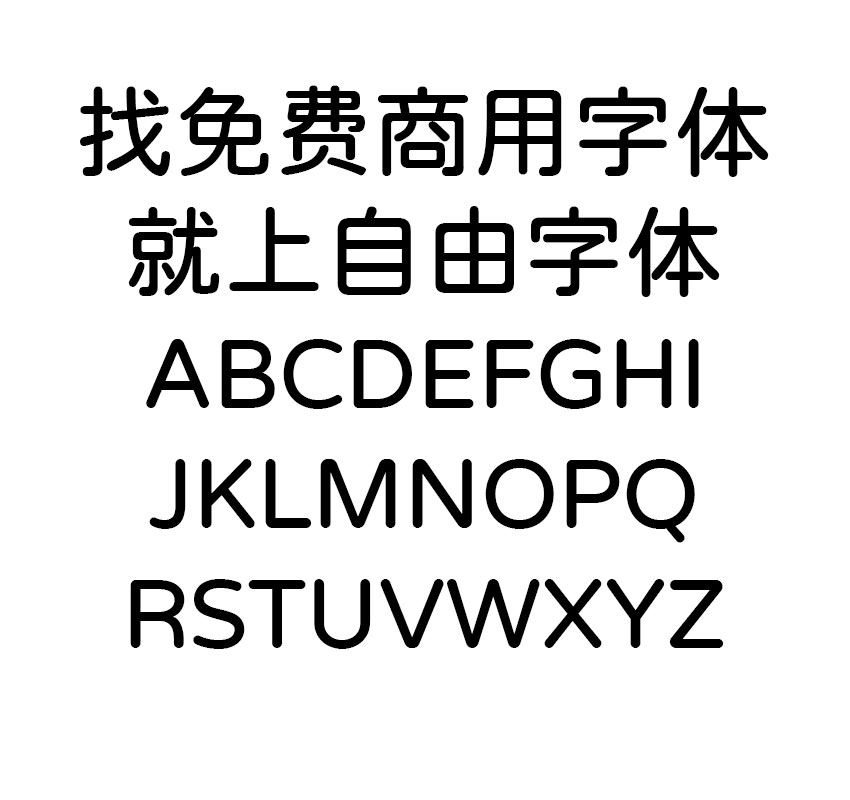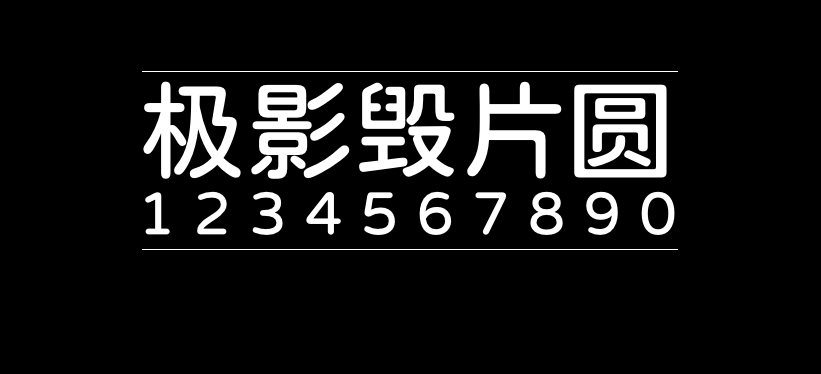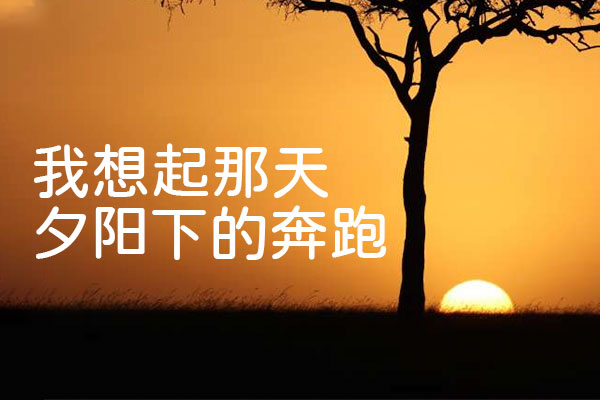
极影毁片圆
极影毁片圆是中国大陆的九阳飞羽在小衫圆体、思源黑体的基础上修改而成的字体。
本字体以jf open粉圆为底本,使用江城圆体3.0、狮尾圆体SC作为增补,补全了Unicode的中日韩统一表意文字,并且根据通用规范汉字表,修正常用的简体字的笔画所整理而成的字体。
值得一提的是:本字体支持简体中文、繁体中文、日语,字体的定位就是整合和补缺,所以基本没有缺字。
作者整理本字体的初衷,是很多媒体视频的字幕制作,都在选择圆体作为主字幕正文。随着B站UP主、Youtuber等自媒体的逐渐兴趣,能够有一个适合的视频字幕正文显示的字体,使大家更方便地“毁片”是一件很好的事情。
由于主要考虑是使用字体在字幕显示,所以本字体暂时仅有Medium(500W)这一种字重。该字体在部分软件中显示为Medium,如果安装后找不到,可以留意下。